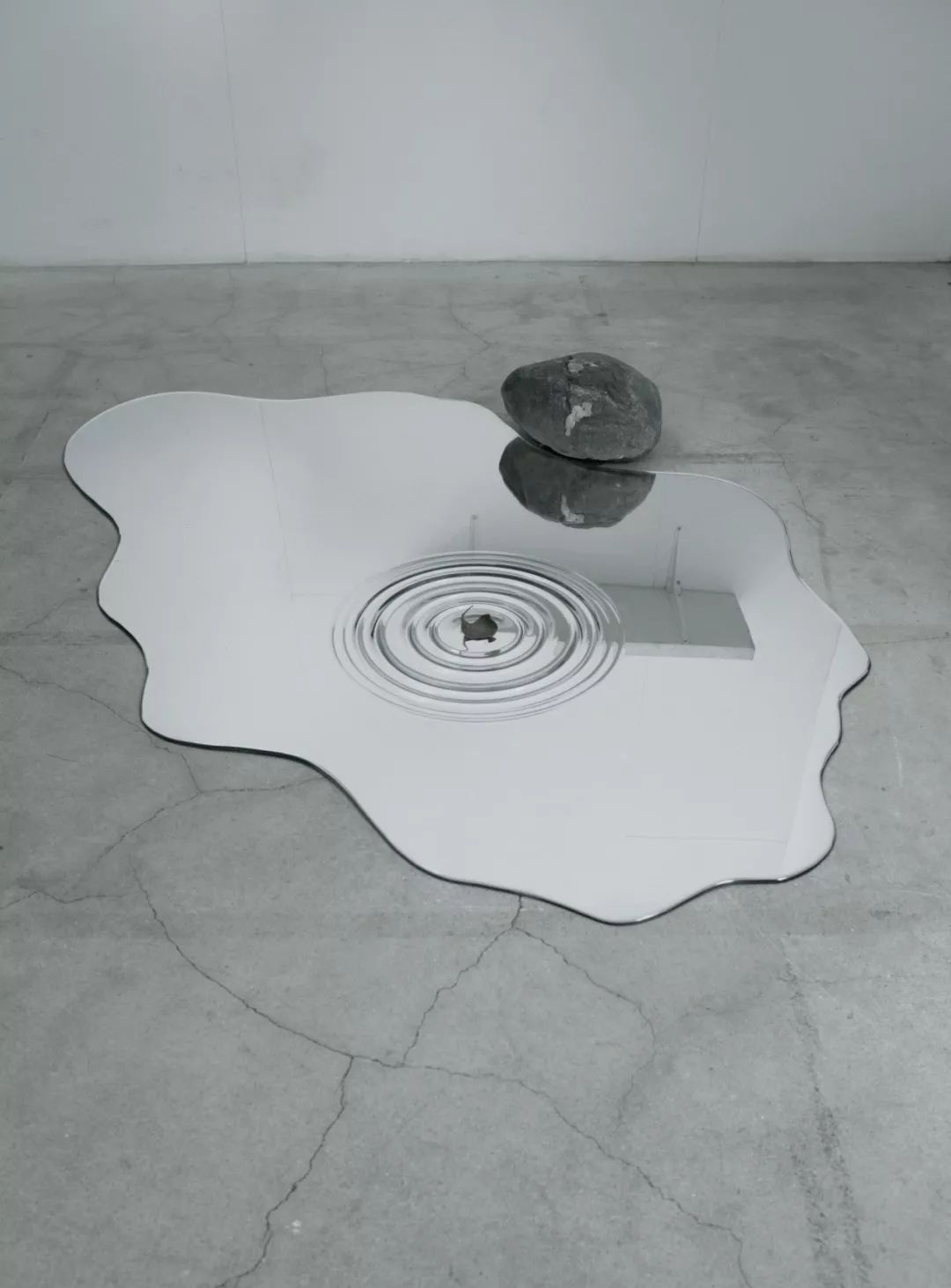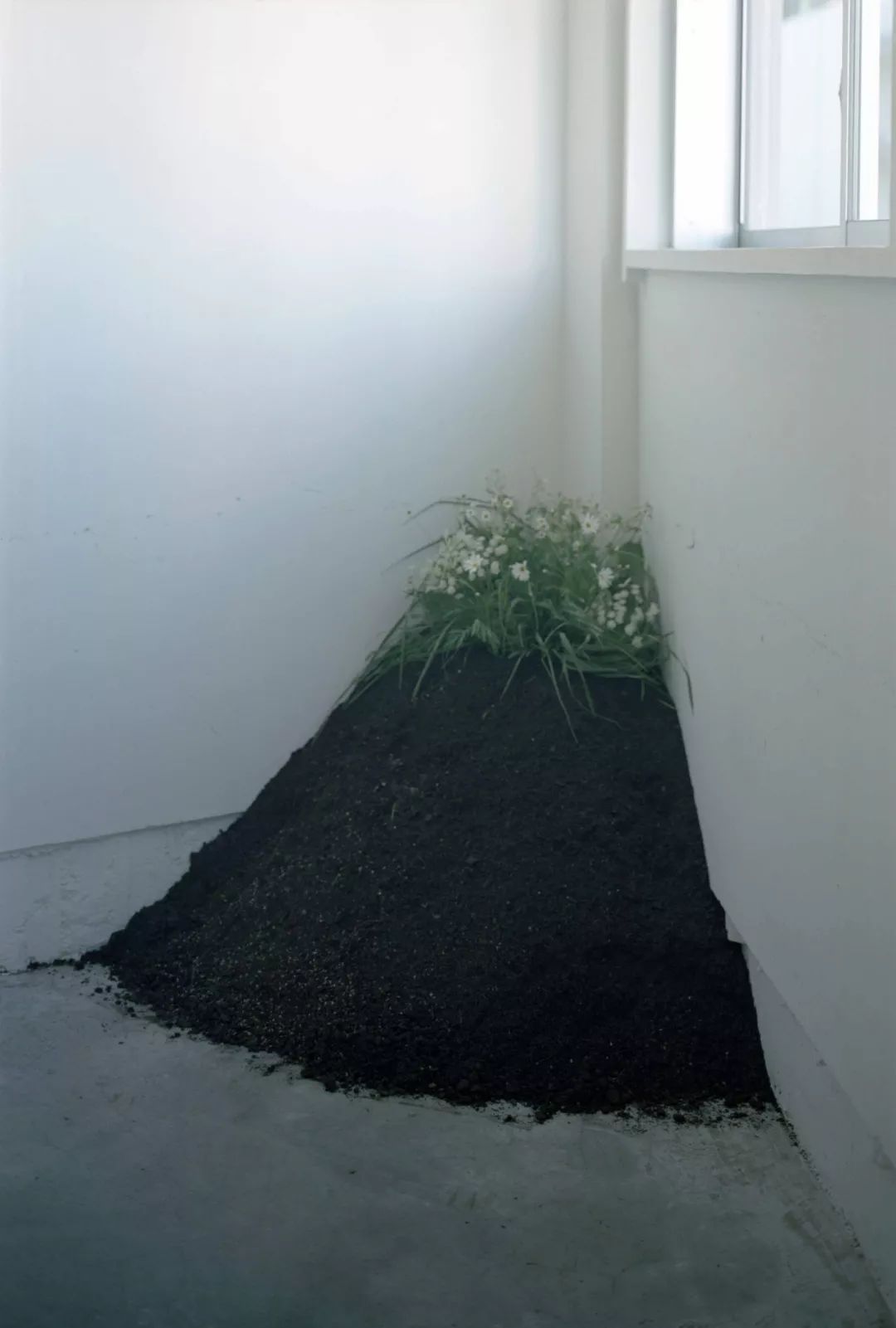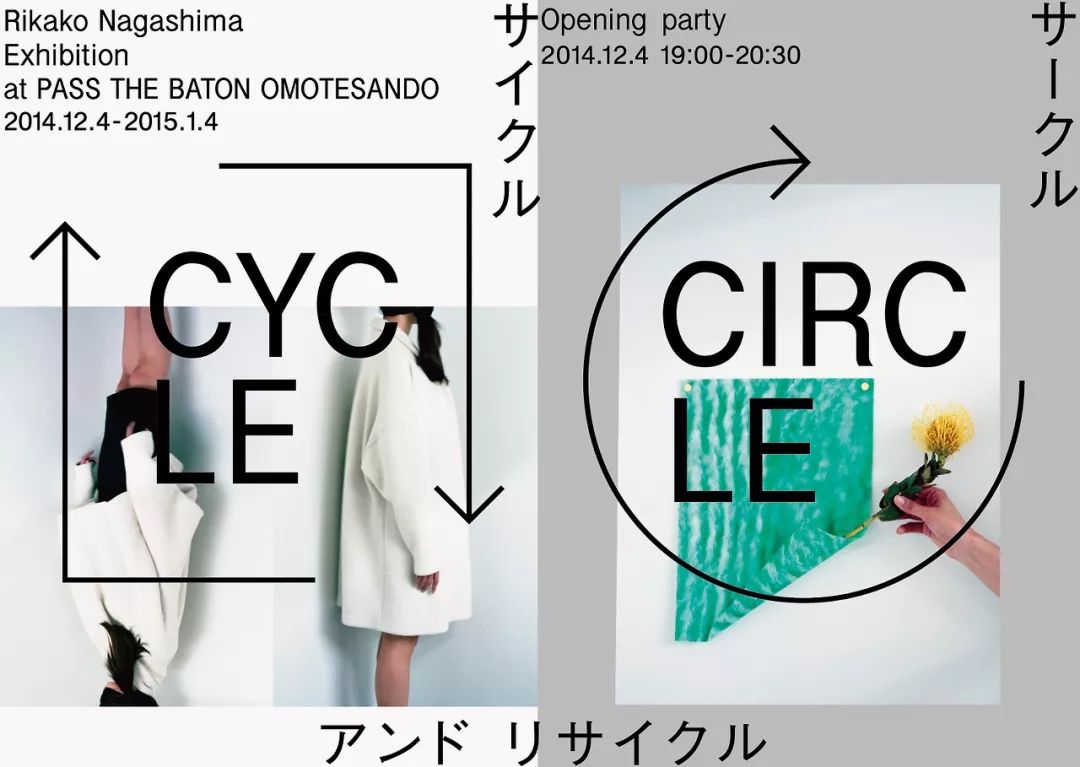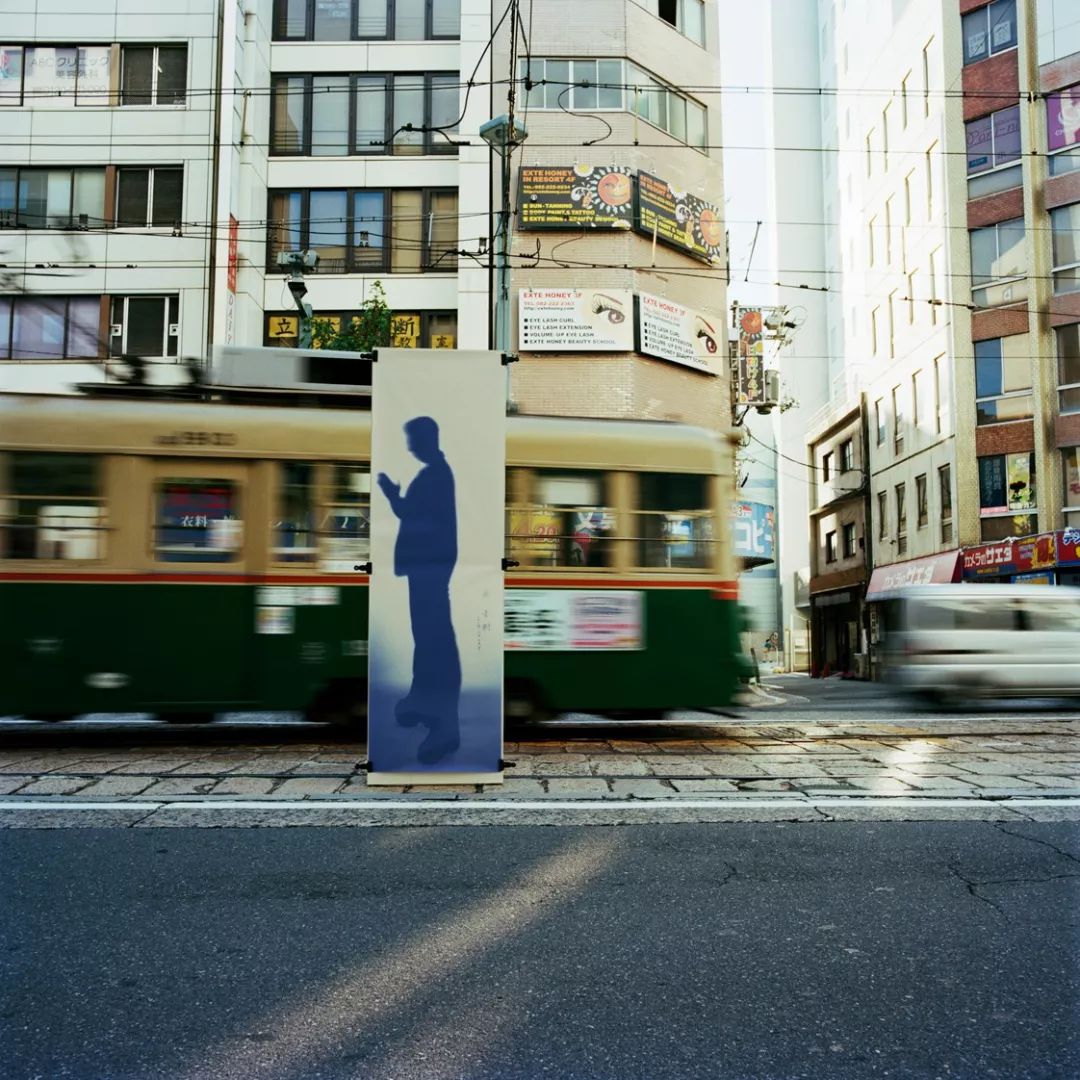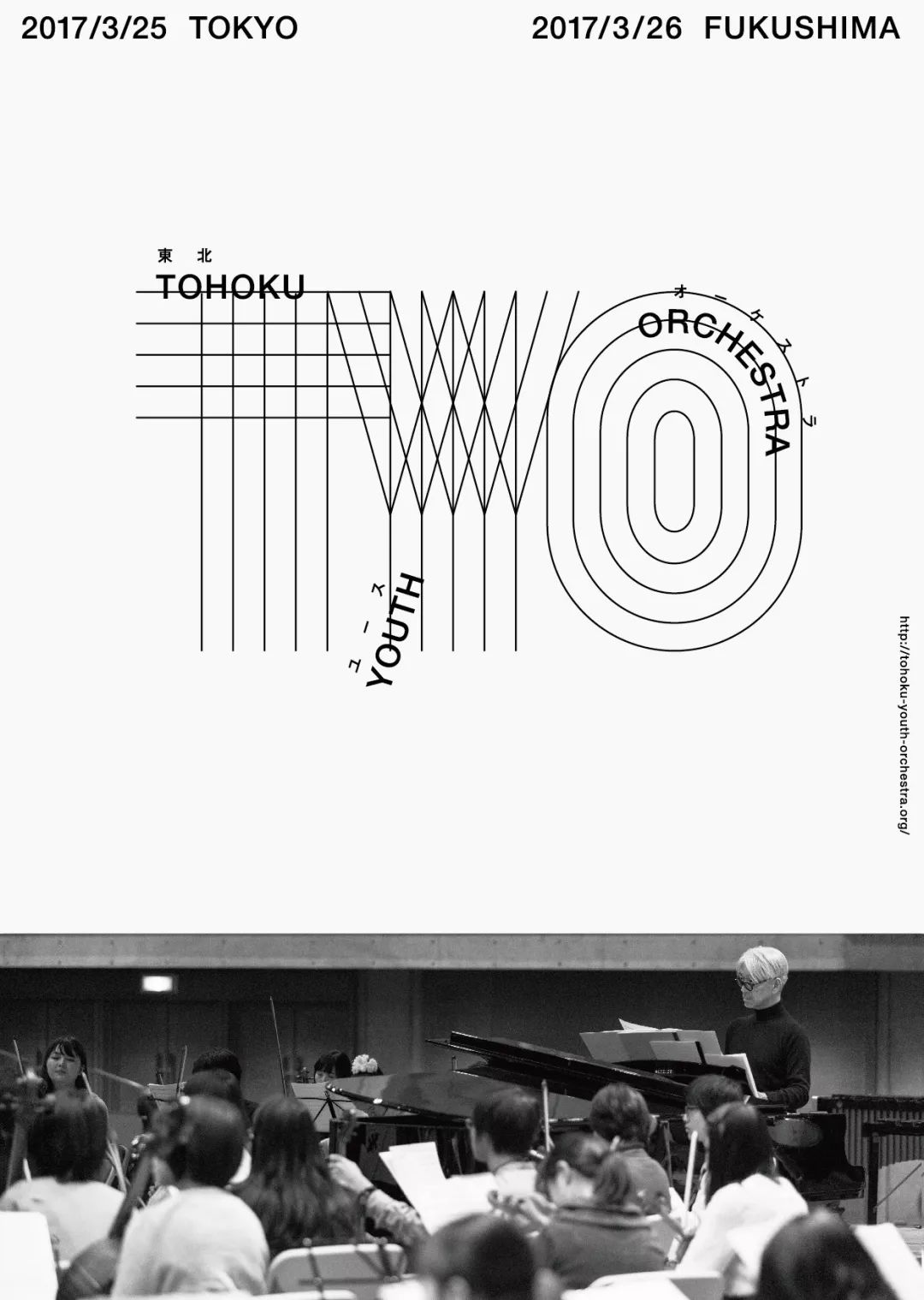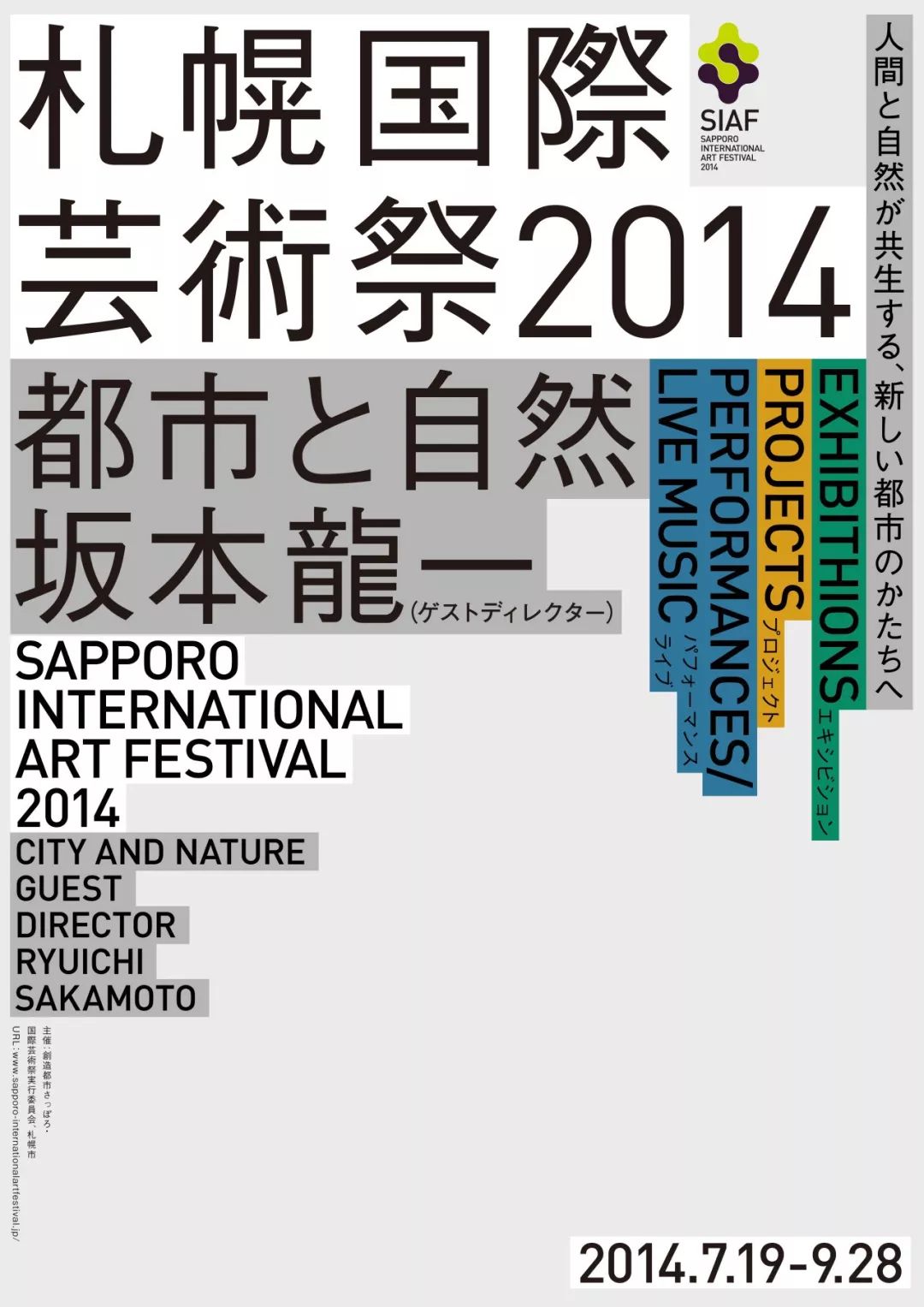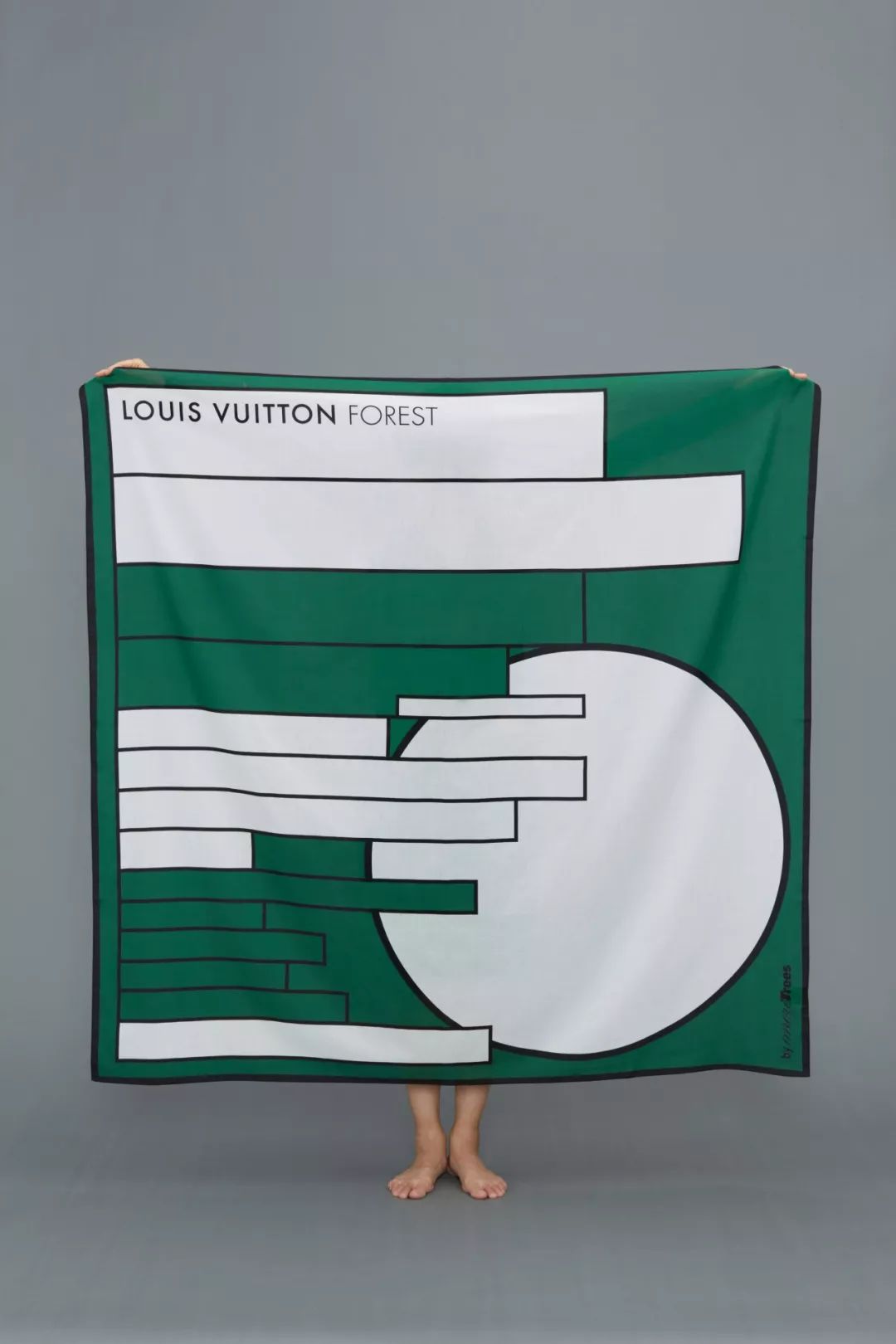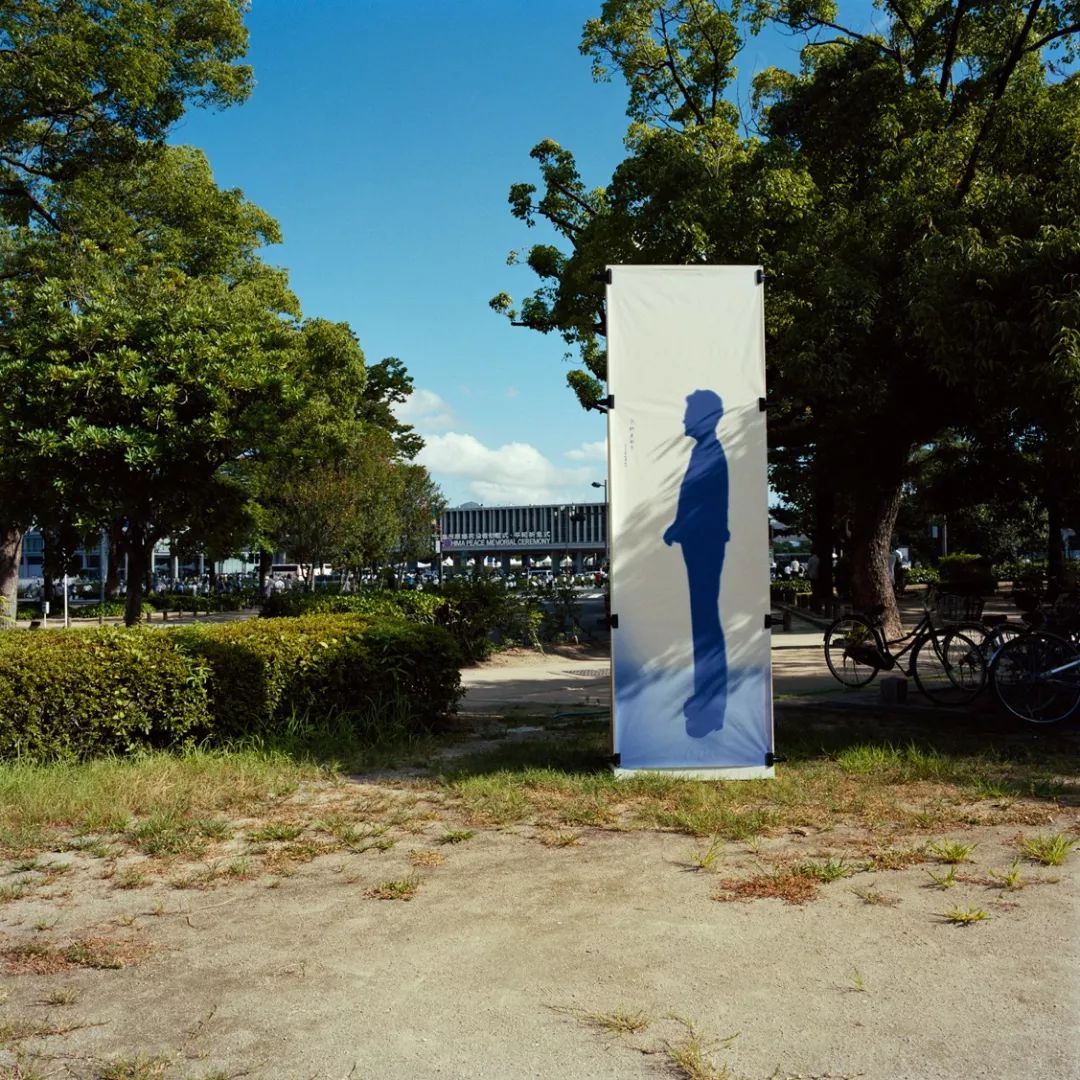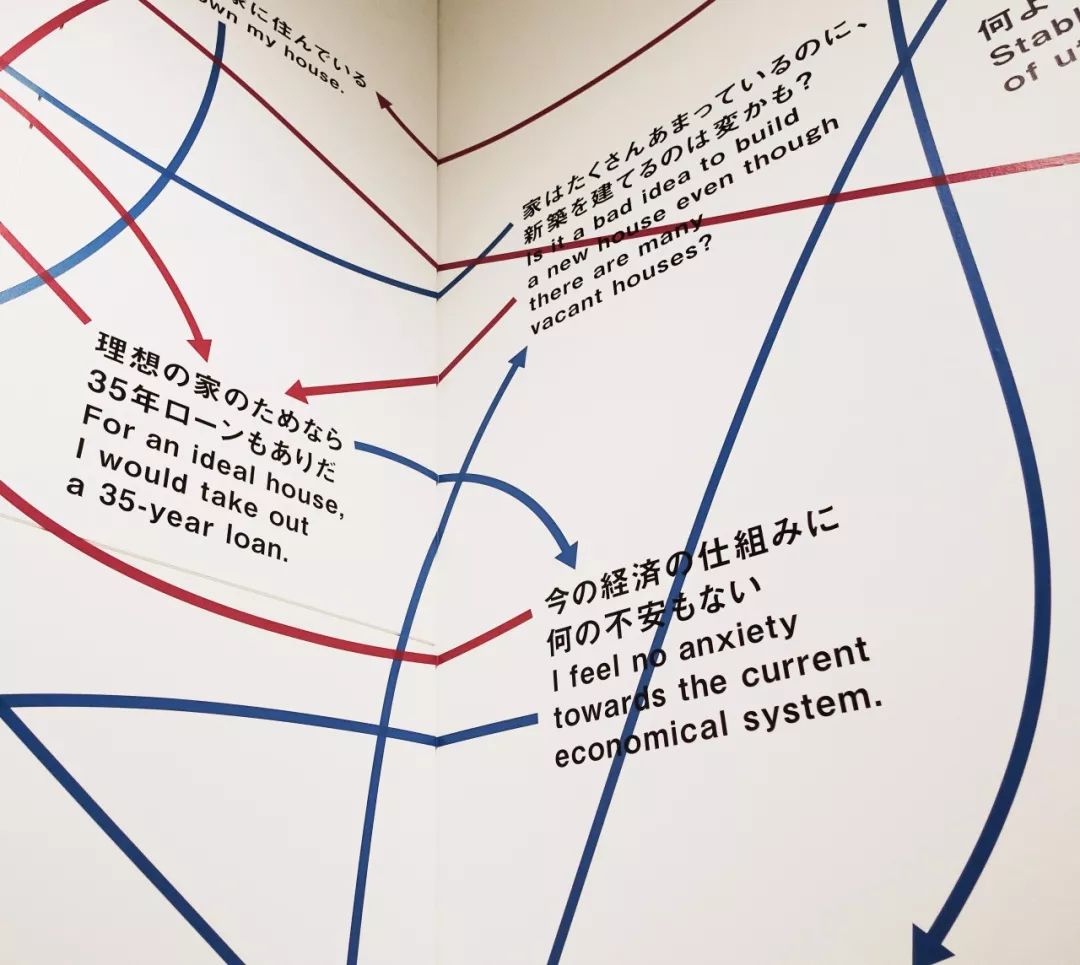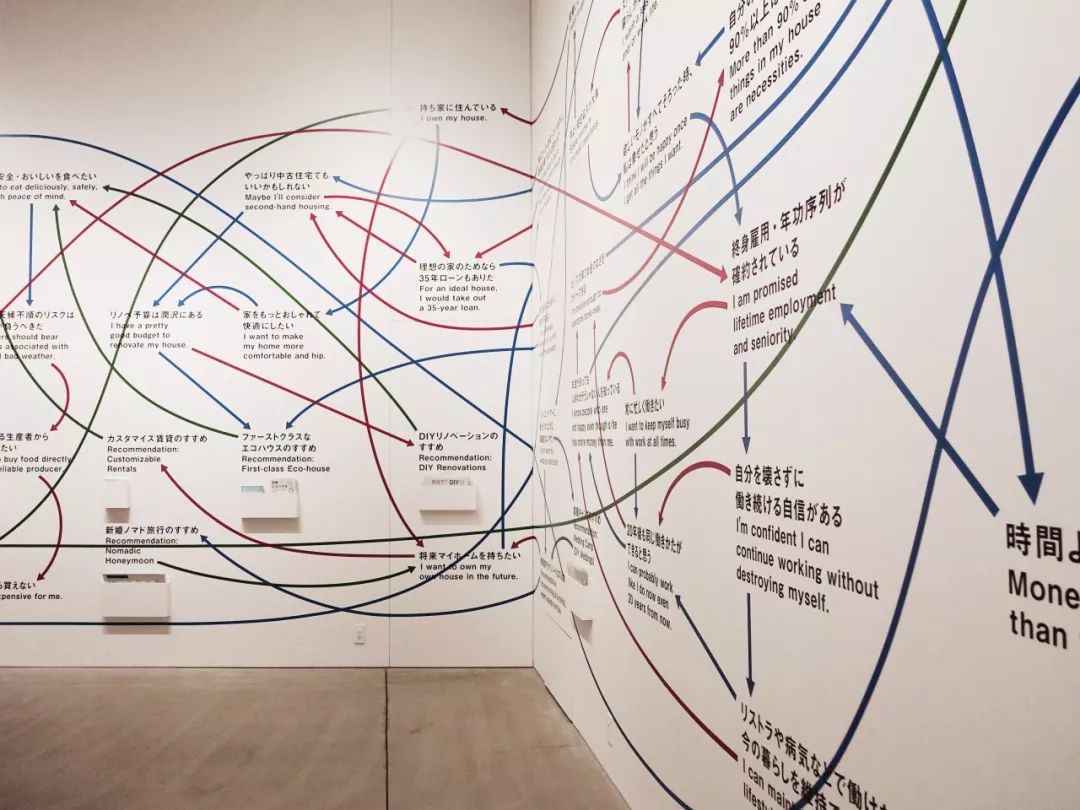
这位日本天才女设计师,用平面设计改变社会
长嶋Rikako,是一位出生于日本茨城县的80后。她于2010年斩获了日本平面设计师协会(JAGDA)新人奖,刷新了该奖的最低获奖年龄,并一跃成为日本设计界最受瞩目的新锐设计师。除此之外,她还曾斩获过纽约ADC特别贡献奖、每日广告设计奖、东京ADC 奖等多项设计大奖。在这些耀眼的光芒背后,谁都未曾想过,这位日本设计界的天才少女,其实是从一个连谷歌地图都搜索不到的地方,一步一步地走出来的。
WATER MIRROR
长嶋Rikako 出生在日本茨城县的乡下,她从小同祖父母、父母、哥哥、姐姐生活在一起,是一个7人组成的大家族。由于家境贫寒买不起玩具,长嶋只能自己动手制作。她的玩具素材大多取自大自然山林里的竹子做成的弹弓、和纸和竹子做成的风筝等。在制作完之后,长嶋还会精心地给每个玩具涂上自己喜欢的颜色。正是在这种后天环境与自身天赋的共同作用下,长嶋不知不觉地走上了设计的道路,并进入日本顶级美术大学武藏野美术大学进行专业的学习。2003年毕业后,她进入了博报堂工作,担任佐野研二郎的助理,并在此期间逐步展开了个人职业生涯。
HOUSE PLANT
长嶋活跃的领域远远超越了单纯的平面设计,还涉及展场规划设计、商品包装设计、视觉传达设计等等。她曾接手大贯卓也和已故的设计才女野田凪(Nagi Noda)为原宿Laforet 百货设计年度平面广告;也曾替登陆日本的著名的手工巧克力品牌伊万・瓦伦丁(Yvan Valentin)设计包装;还曾和日本时尚品牌三宅一生合作设计过包包……长嶋的设计灵感多来源于自然,她擅长运用字体的多样性及色块的冲突性来进行创作,轮廓简约明朗而又大胆美丽,极具视觉感染力。长嶋的作品模糊了设计、当代艺术和时尚之间的界限,为平面设计创造了更多的可能性,而这些新的可能性则足以证明她的实力。
interview 长嶋Rikako
「我希望我的作品有益于自然环境,有益于文化,有益于社会上的弱者,这也是我的作品的意义所在。」
长嶋 Rikako
设计师。1980 年11 月11 日生于茨城县,2003年毕业于武藏野美术大学视觉传达设计系,后在博报堂工作。2014 年创建设计公司village®。以平面设计为基础,广泛展开品牌、CI、VI、产品设计、包装设计、编辑设计、艺术指导等工作。与梅赛德斯奔驰时装周、2014 札幌国际艺术节、BAO BAO ISSEY MIYAKE、ZUCCa 等展开了诸多合作。曾获得戛纳设计奖银奖、纽约ADC 奖银奖、东京ADC 奖、亚洲太平洋广告节大奖、日本平面设计师协会新人奖等国内外诸多奖项。
知日 请问是什么原因促使你选择了设计师这份职业?
长嶋 我在遇到一些不好的状况或者有疑虑时,总是想着要做些什么去扭转这种局面。不仅仅是我自己的事,还有社会上一些不好的状况,我都觉得要用行动来让事情向着良性的方向发展。因此,为了我自己,也为了我所生存的这个世界,我想选择一份能够改变人们价值观、能够发人深省的工作,而平面设计师这个职业刚好可以把我的梦想付诸现实。而且由于童年时期的生活环境,我从很小就开始接触大自然,对大自然充满了兴趣,这一点也与我现在的职业选择密不可分。
CYCLE AND RECYCLE
知日 你在创作的时候,有什么一贯坚持的原则吗?
长嶋 比起思考「怎么去做」,我的重心更倾向于「为了什么去做」。在创作的时候,我希望我的作品能够有益于自然环境,有益于文化,有益于社会上的弱者,这也是我的作品的意义所在。
知日 你现在的创作活动或者创作思想中,有什么是源于童年回忆的吗?
长嶋 我小时候的生活环境,是一个物质极其匮乏的环境。我没有普通小孩子渴求的那种玩具,因此只能自己动手制作。缺什么东西就自己去做,想要什么环境就自己创造出来,这在当时的我看来是理所应当的。我的老家基本上是一种自给自足的状态,到小学和中学去的路上,要骑一个小时的自行车并且翻越两座山,在这种环境下,我每天都能感受到自然的恩惠与严酷。也正是如此,对于我来说,自然就像老师一样,而我创作的核心,就是对自然的敬意。作为环境的那种自然自不必说,还有一种是人类内在的自然(无意识或者混沌的状态),我的创作目的就是指向这两点。
札幌国际艺术节
知日 请问您平时在创作时有什么常用的、爱用的工具或书籍吗?
长嶋 小野洋子的《葡萄柚》(Grapefruit)。在这本书中,小野洋子独特的视点将现实世界中那些稀松平常的事物都变得不再普通,看这本书就像是在给大脑做体操,因此我非常喜欢。除此之外,还有我从媒体艺术家菅野创先生那里收到的小乌龟模型。
我非常喜欢米切尔・恩德的作品《毛毛》,我曾经和菅野创先生说过:「我想像主人公毛毛那样,不去理会资本主义世界的种种规则,而是将自己与自然融为一体,并怀抱着这样的意识去捕捉各种事物。」没想到他在我生日的时候就送给我这个小乌龟的模型。因为乌龟在故事中起着引导毛毛的作用。这个小乌龟就放在我的工作台上,我每天都能注视着它。
知日 你独立的企划项目「Human_Nature」(人性) 从2013 年开始启动, 请问这个项目的设计理念近年来是怎样变化的?
长嶋 我们所生活的这个社会,有着秩序与混沌、有意识与无意识、都市与自然这样矛盾的存在,而我们人类存在的价值是不是正蕴含在对这些矛盾的调和之中呢?我想从这个问题入手,举办一些专门面向城市居民的活动,来唤醒人们对混沌、无意识、自然这种存在的关注,同时让人们认识到这些状态也存在于自己的内心之中。这个理念是我从未改变的。今后,随着人工智能的发展,社会将会发生一些变化,我还想根据这些变化为「Human_Nature」的内容再增加一些含义。
向卡普尔致敬展
知日 你设计的作品中经常会有「自然」元素的存在,请问你是怎么定义自然的呢?
长嶋 如果把「城市」看成人们有意去创造出来的具有秩序性的存在,那么「自然」就是一种不含目的的、混沌的、无意识的存在。对于人类来说,与我们最亲近的自然物其实就是人类本身,因此我们应该和自然一样,身心怀抱着一种混沌的状态去生活,但是这种状态在都市生活中是很难见到的。无论是街道的形态、生活的方式,还是内心的情感都应该如此,然而事实上一旦有什么东西乱掉,我们就常常会强迫自己将其按照类型、规则整理出来。
生活方式冒险家「无尽的自问自答」
知日 近些年你创作的作品中,很多主题都与音乐相关,这是出于什么原因呢?关于这些作品是怎样思考的?
长嶋 我的设计会随着创作目的的改变而改变。在和音乐家坂本龙一先生合作时,坂本先生的很多创作都是想要通过音乐将自己的思想展现给大家,例如他对政治活动、东北支援活动或是环境问题的关心等,而我所要做的,就是作为他的思想的翻译者,全心全意地将他的各种姿态表现出来并传递给世人。而在和那些年轻的音乐家们合作时,我的重心主要放在如何将他们的音乐观表现出来这点上,然后再添加一些身体性的创作,就像是在听到音乐之后自由、随心地给每个音符涂抹上颜色。
TOHOKU YOUTH ORCHESTRA
知日 在你看来,设计应该具有变革社会的力量。你的作品是如何基于社会背景创作出来的呢?
长嶋 设计的确具备改变世界的力量,这个世界上也的确存在着这样的设计师与作品。但是就我个人来说,我无法说出这样大的话,我觉得设计是一种可以改变人们观察这个世界的目光的存在。我有一些工作是基于社会现实来创作的,相比于工作,可能称作艺术作品更为恰当。这其中之一便是我和现代艺术家宫岛达男等人共同参与创作的活动「PEACE SHADOW PROJECT」(和平之影计划)。这个创作活动中,我们将广岛原子弹爆炸幸存者们的影子拍摄下来并制作成蓝影图片,然后将图片放置于当时(1945 年8 月6 日)发生原子弹爆炸的地点,并拍摄成一组组照片。在活在当下的人们看来,照片上的场景可能就是一些司空见惯的街景。然而,这些原子弹爆炸受害者的蓝色影子,却向我们诉说着眼前的这些日常不是理所应当的存在,而是一个个和平的奇迹。
PEACE SHADOW PROJECT(和平之影计划)
还有「Relight Project」(重燃计划)也是这个类型的创作活动。从2011 年3 月11 日发生东日本大地震至今,长年累月发生了不少的变化,「Relight Project」这个创作活动就是将这样一个多样的3・11 东日本大地震以视觉化的方式呈现给大家。关于3・11 东日本大地震,人们的记忆会逐渐淡化,价值观也会改变,有的人抱着乐观的想法,有的人则有着不同的意见。因此,我想通过这个作品提醒大家无论是选择复兴还是选择忘却都要抱有怀疑,不要持一边倒的态度。与此同时,我也想通过这个作品来唤醒人们对3・11 东日本大地震的关注。
Relight project